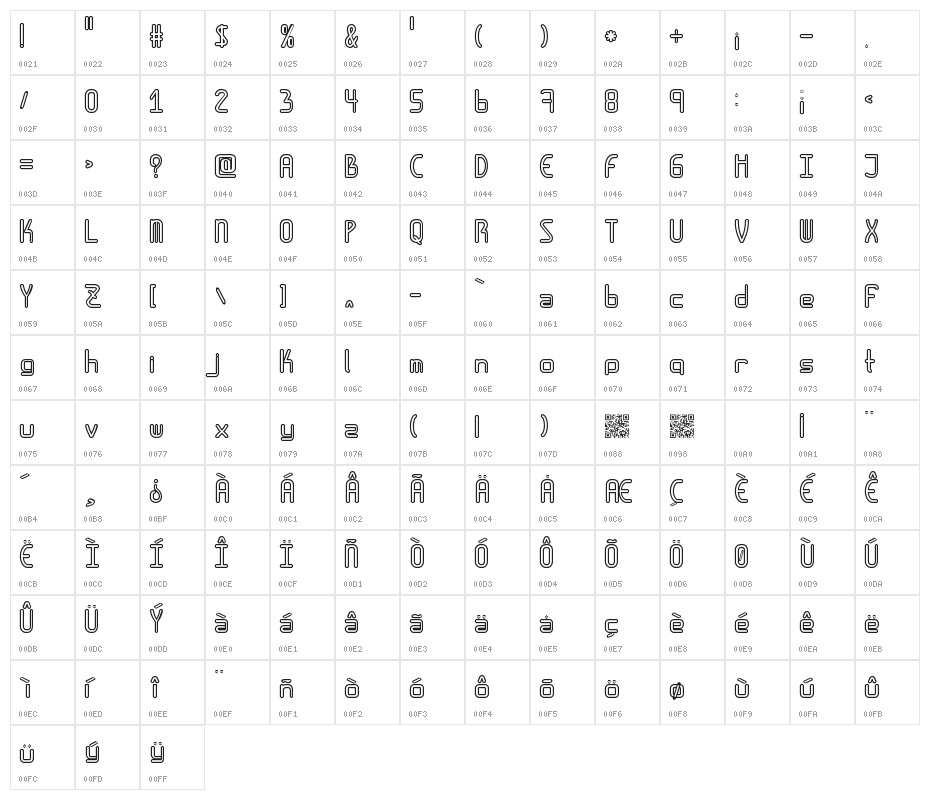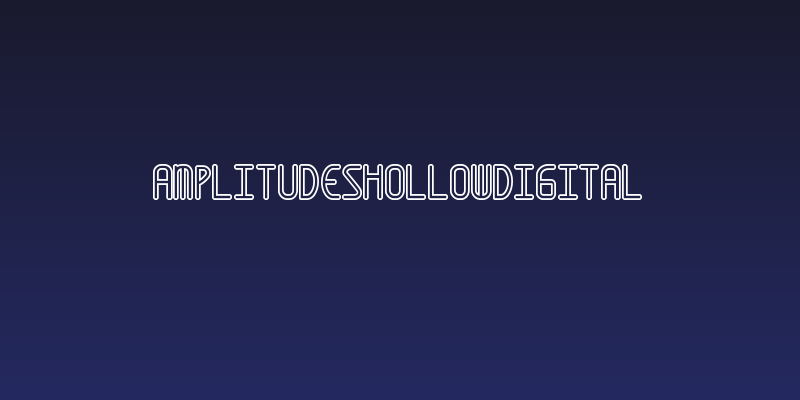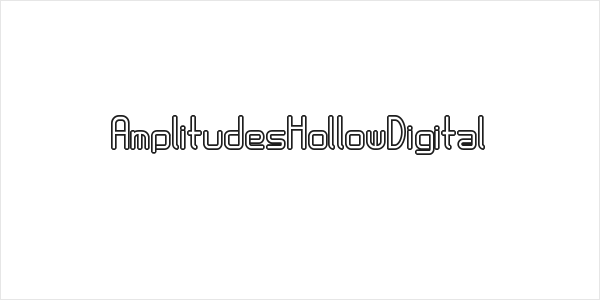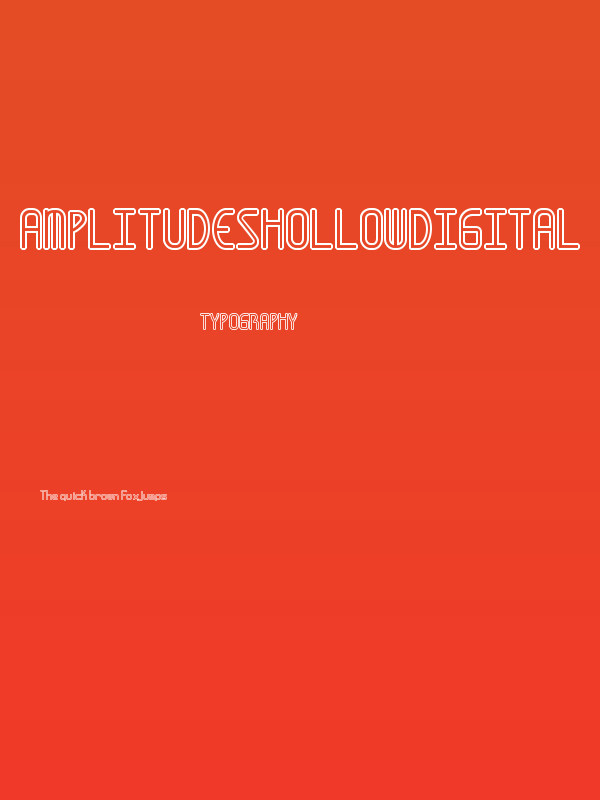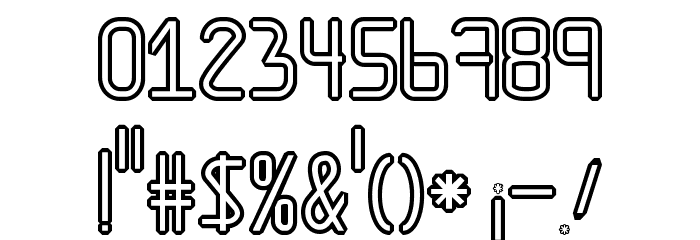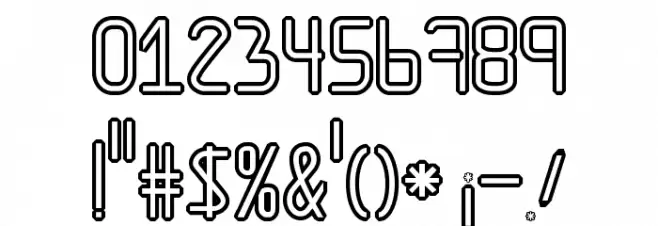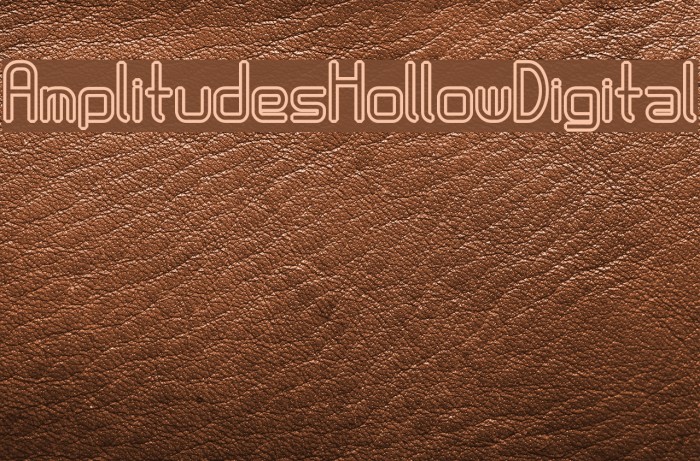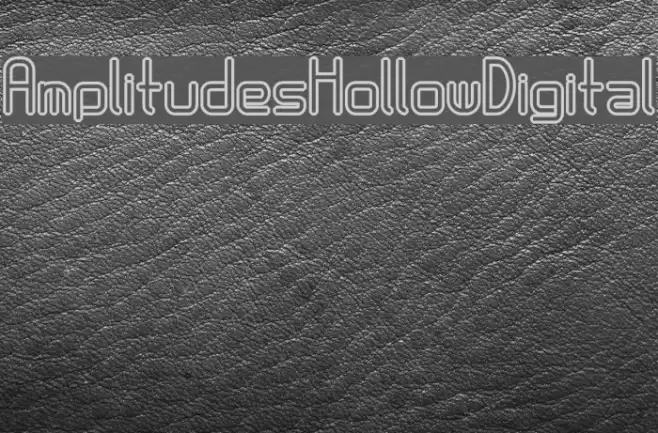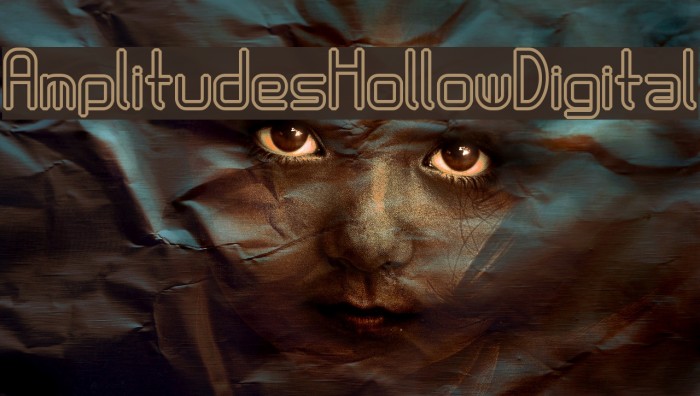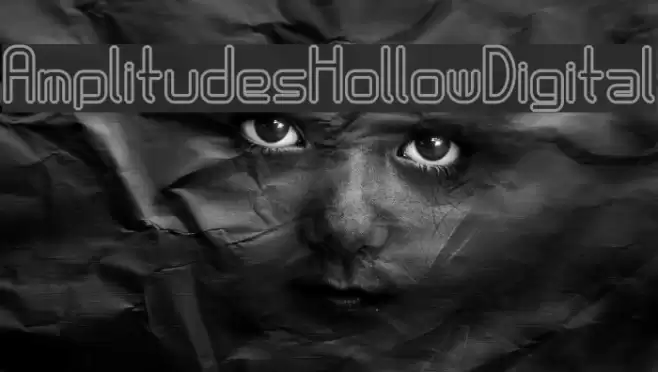
AmplitudesHollowDigital Font
✎ Outline
| Anwendungsfall | Logos, Headlines, Digital interfaces |
| Vorgeschlagene Projekte | Ideal for digital interfaces, tech branding, futuristic posters, and modern advertising. |